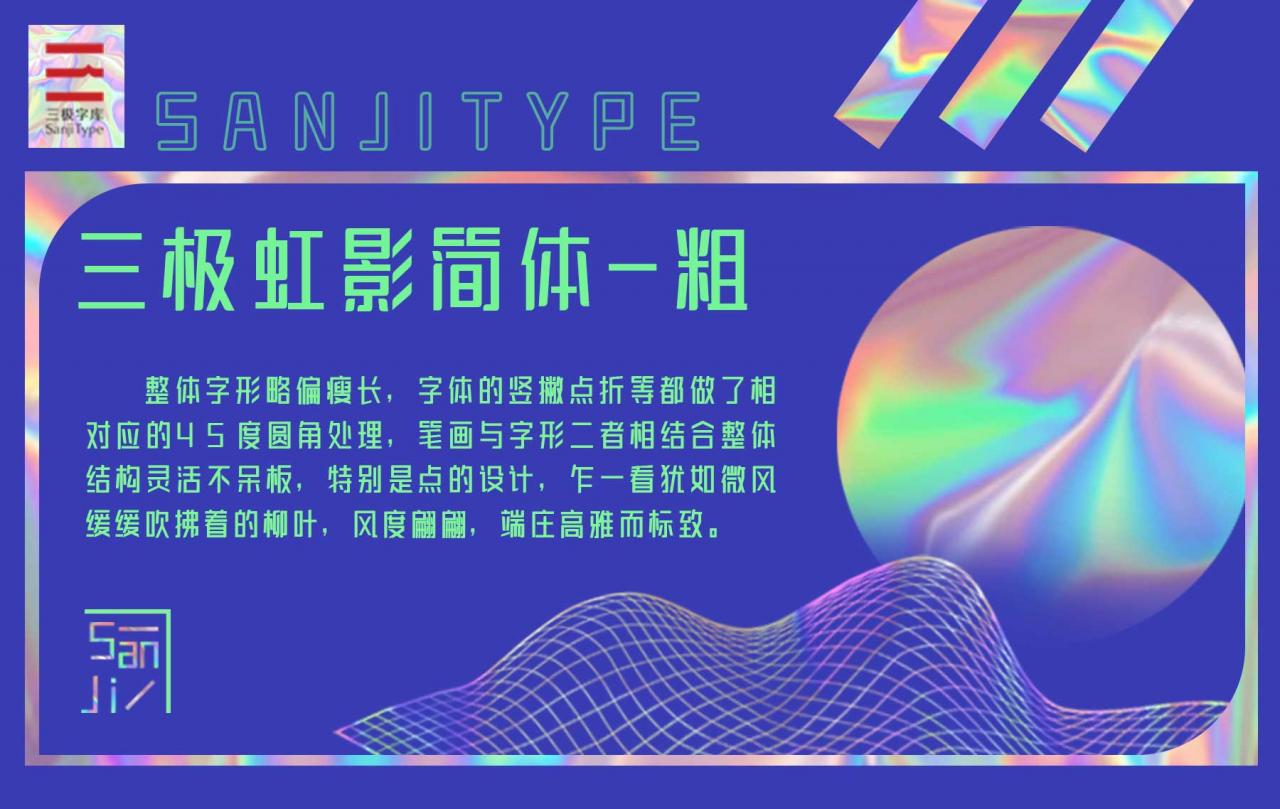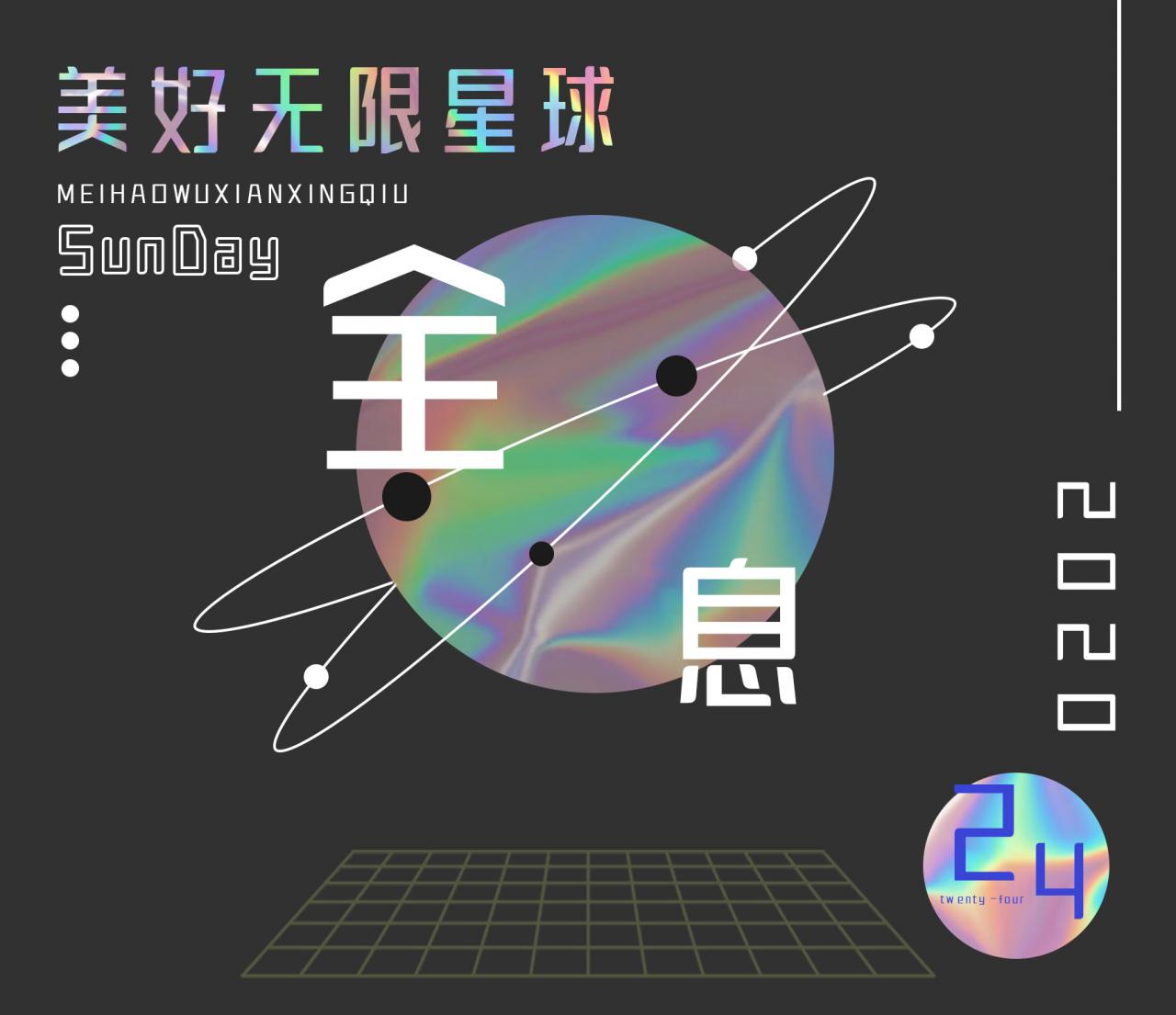
三极虹影简体-粗
字体名称:三极虹影简体-粗
设计师:罗碧霞,庞丽珊
三极虹影简体整体字形略偏瘦长,字体的竖撇点折等都做了相对应的45度圆角处理,笔画与字形二者相结合整体结构灵活不呆板,特别是点的设计,乍一看犹如微风缓缓吹拂着的柳叶,风度翩翩,端庄高雅而标致。本款字体适用于报刊杂志,书刊、品牌广告和产品包装设计。
适用媒介:杂志、书籍、广告、海报、宣传册、包装、影视、动漫、交互设计。